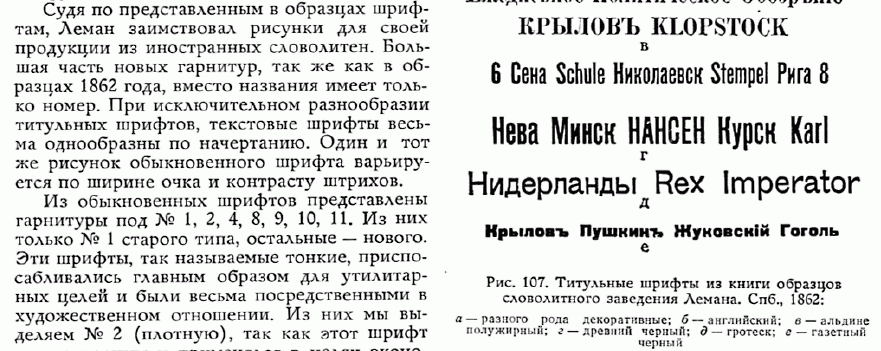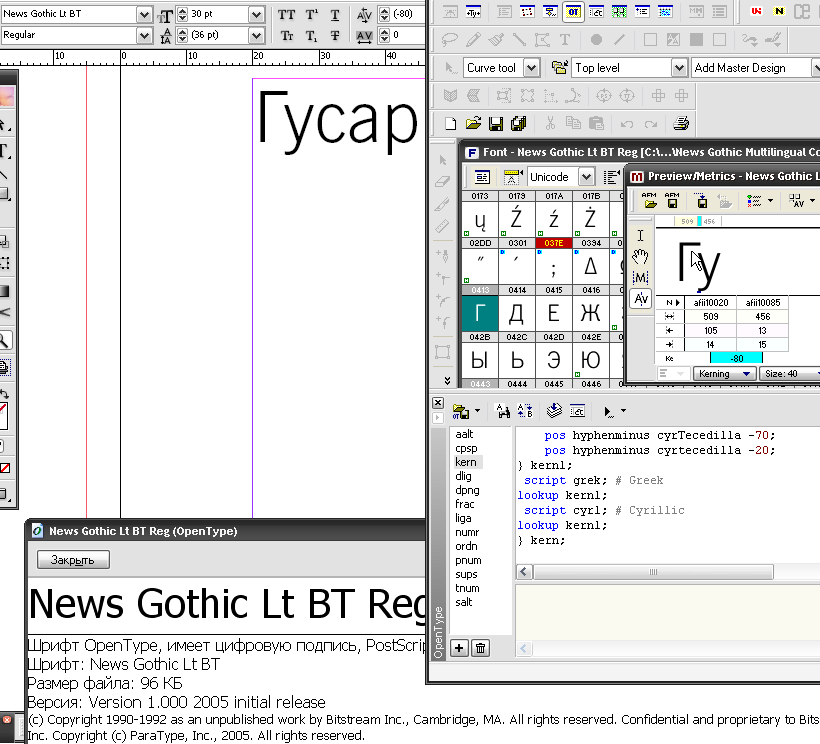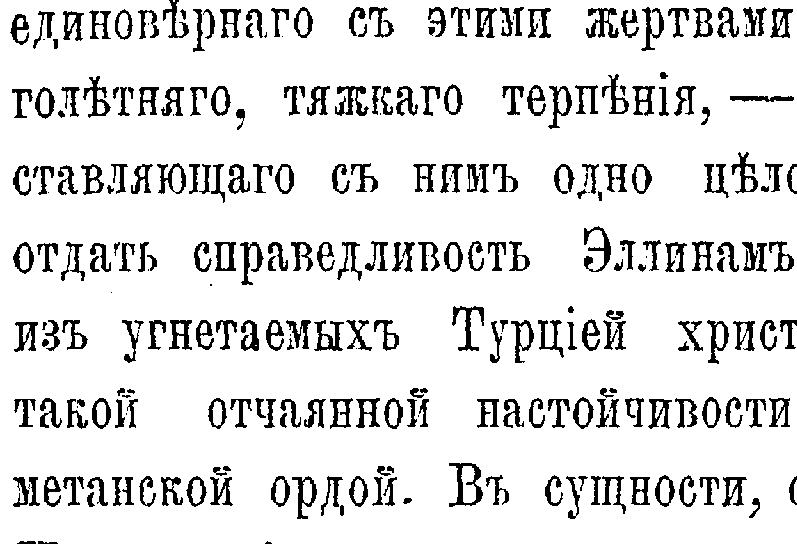
Gusar
где есть кириллический кернинг, нет в фиче определения
все уже там есть давно и как надо работает.
Дык это самопал. Да и чего меня убеждать, если я четко написал, нет конкуренции, поэтому ..
У меня так
Artemius делал не Тема
Что там на картинке я не вижу, догадываюсь что какой-то паратайповский OTF с нерабочей фичей, больше они так не делают.
Больше такого полного набора начертаний нет ни у одной компании в России. Купить шрифты из гарнитуры Artemius нигде нельзя. -- ишь ты, панимаешь. Прям как у пиндосов. Майкл из Алабамы и Билл из Техаса -- всё! чемпионат мира проводится.
Кстати, "словолитное заведение Лемана" -- чего-то русскость Лемана вызывает некоторые сомнения.
1877 год. Москва. Типография Родзевича.
Какая разница русский Леман или индеец, заведение его находилось и работало в России
В отрывке же сказано, что заимствовал из иностранных словолитен, а не прогулялся до Троице-Сергиевой Лавры и не позаимствовал там. А вот русские художники ходили и заимствовали, по крайней мере, традиции.
И так для справки: в Германии этого же периода много кого работало, но готика была превалирующей. Традиция, мать ее. (я об эту готику во время учебы глаза сломал).
Правда, МК в Кварке... это издевательство над шрифтом заголовков делать - раз плюнуть.
Испортить шрифт легко в любой программе. На мой взгляд яблочко от контрола (Ctrl) недалеко падает. Иногда такие вещи получаются случайно.
1877 год. Москва. Типография Родзевича.
И что? Это пример вдохновления лаврой?
в Германии этого же периода много кого работало
Леман в Петербурге работал
индеец-книгоиздатель
Какой издатель, он шрифты делал, а не книги издавал
1) Таким же шрифтом (и многими другими) сделан Троицкий патерик для общего чтения, собственная типография, 1896 год.
2) Работал в Петербурге -- значит должен был соблюдать наши традиции, как это делали многие другие, работавшие в Германии. (Чего тут непонятного? Восприятие культуры страны проживания (ассимиляция по простому). Соборы в Кремле тоже иноземцы строили они что сильно готику напоминают?)
3) Бог с ним.